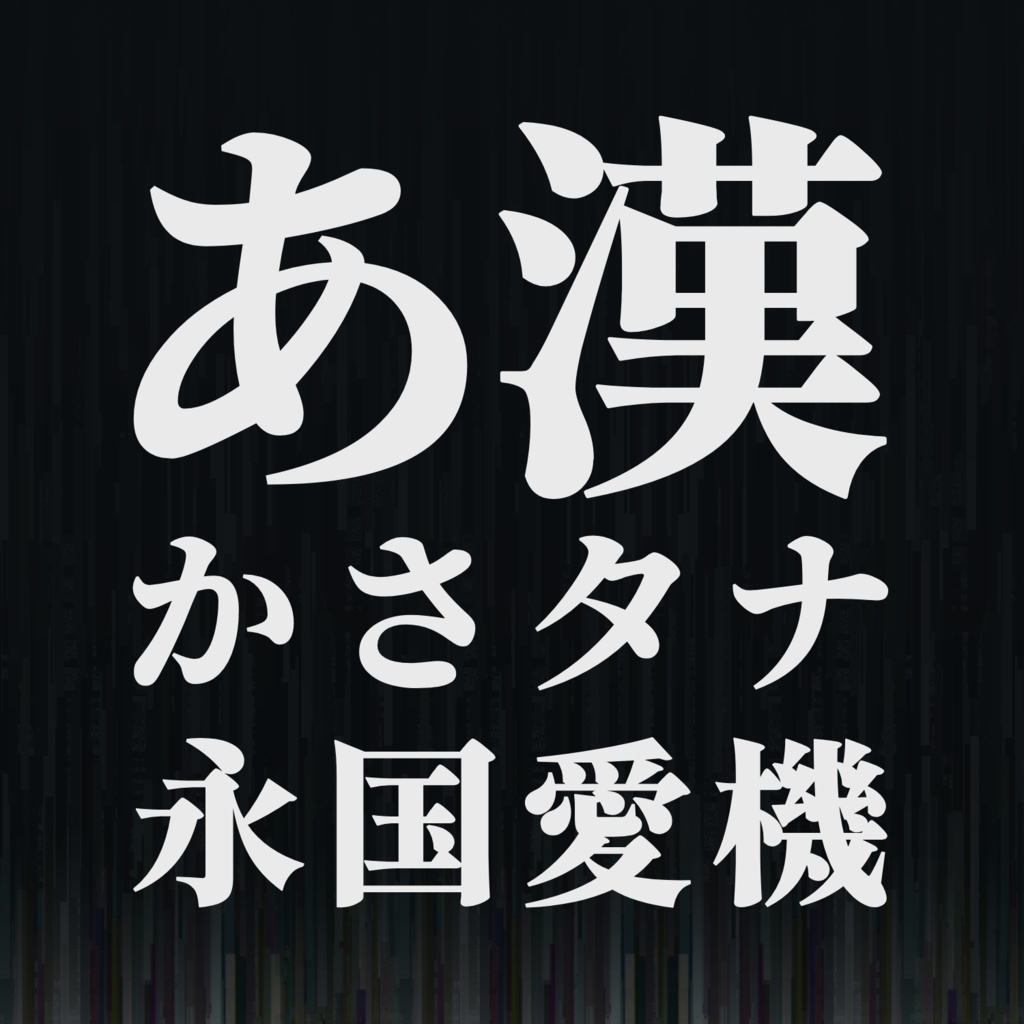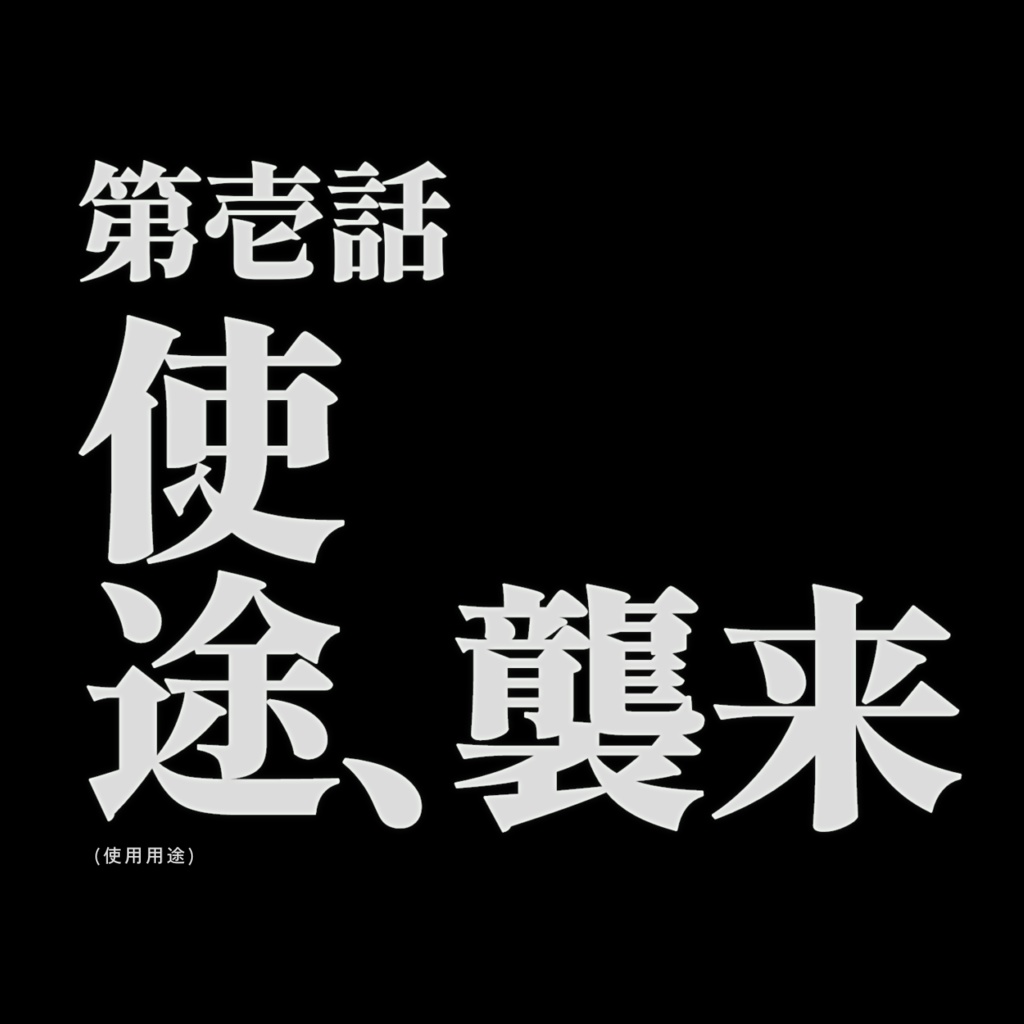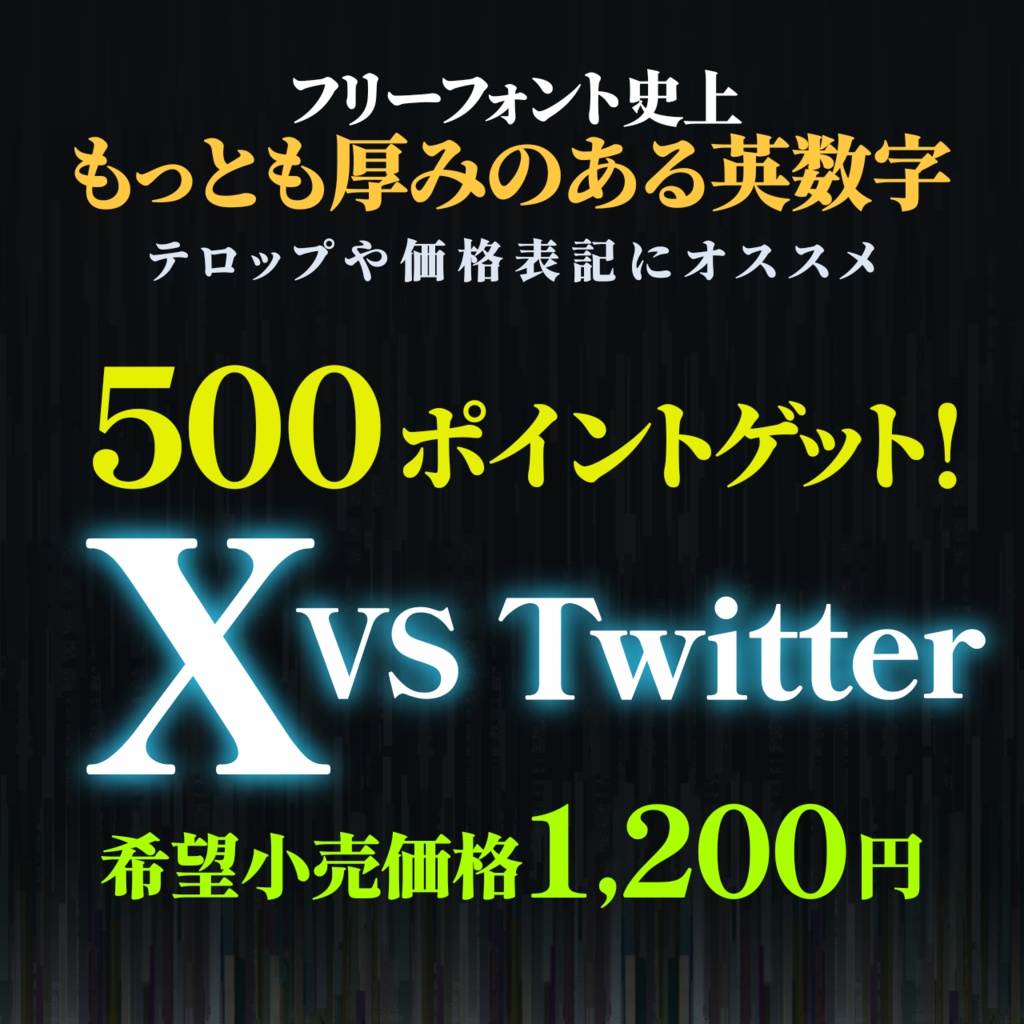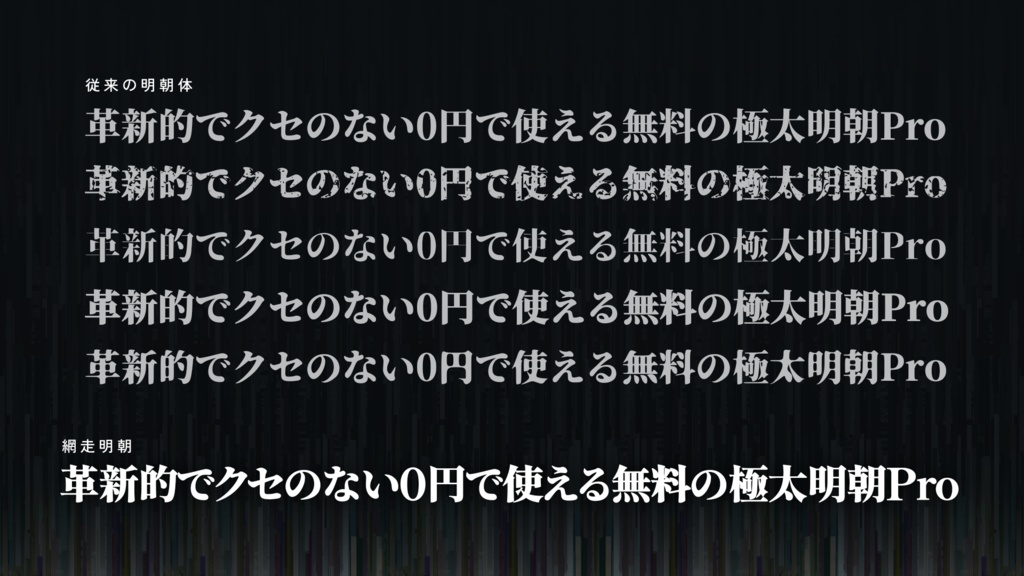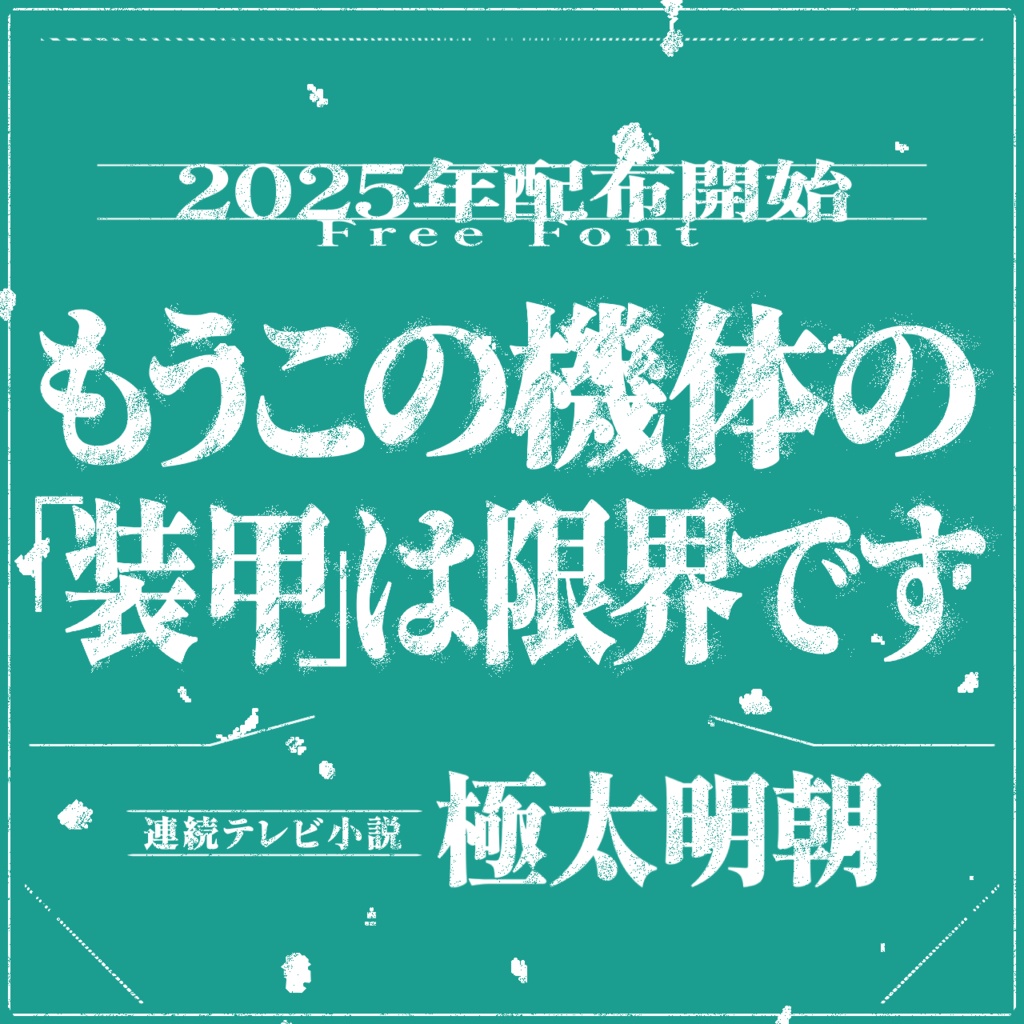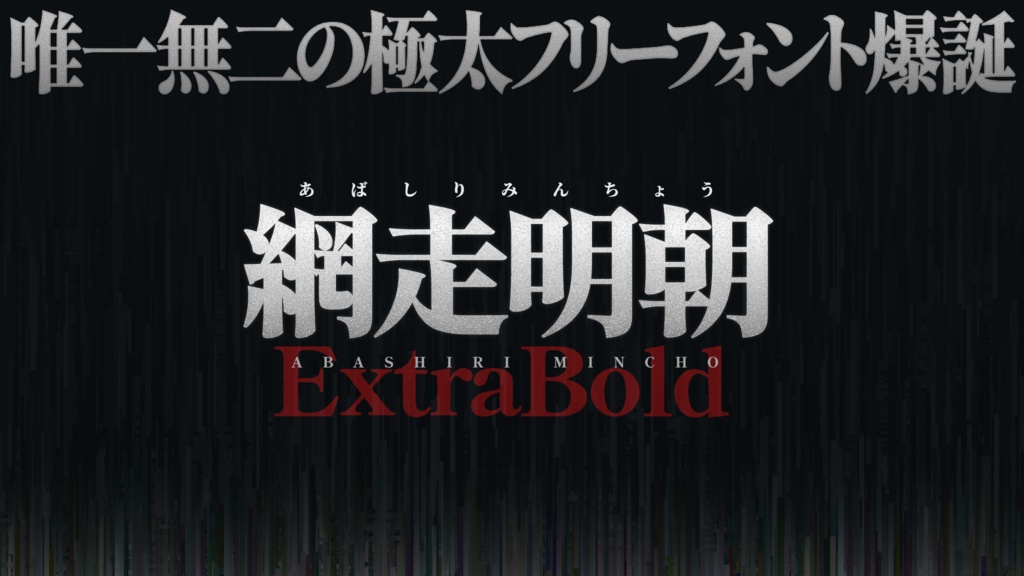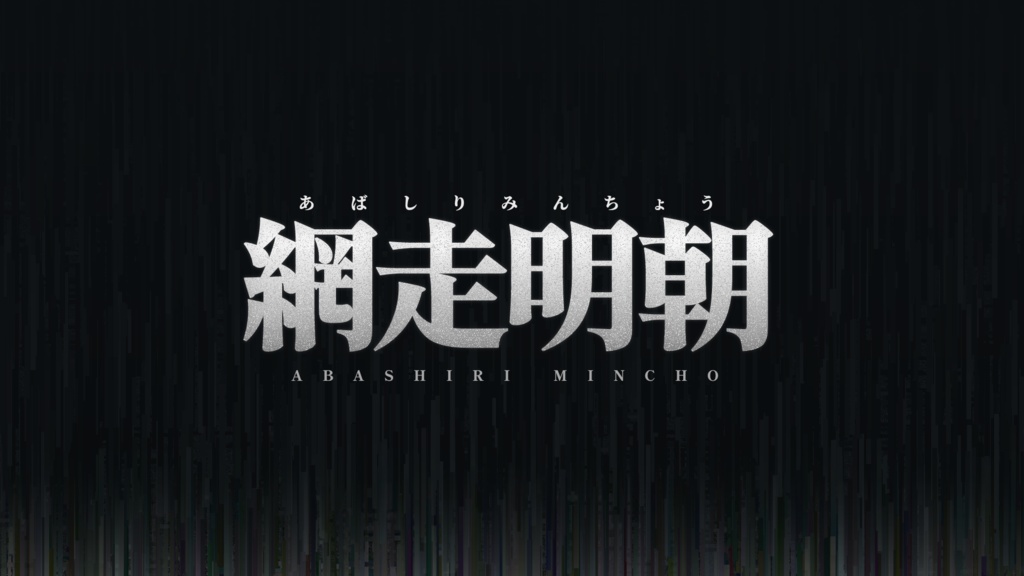
【フリーフォント】網走明朝
完全フリーの極太明朝体です。 あらゆる漢字が使えます。 商用利用もご自由に。 SIL Open Font License 1.1のもとで改変・再配布も可能です。 ■フリーの明朝体フォントで"史上最太"を実現 見出しやテロップなど、源ノ明朝 Heavyそのままでは太さが足りない場面で有効にお使いいただけます。装甲明朝や源界明朝の代替としても便利です。 ■バラエティなどでよく見るフトコロの広い英数字 フリーフォントが安っぽく見えがちな原因のひとつでもある従属欧文。網走明朝では、マティスEBを参考にした「厚み」を持たせることで、日本語の文中でも存在感を際立たせます。価格表記や点数表示にもオススメです。 ※画数の多い文字では潰れる可能性があります。重要情報の記載や本文での使用は非推奨です。 ※縦書きには非対応です。 スペシャルサンクス - 源流明朝 H - しっぽり明朝 Extra Bold - BIZ UDP明朝 Bold [2026.08.10]ver1.10 ライセンス表示および予約フォント名を整理し、OFL.txtなどの関連文書を同梱。フォント内部のライセンス情報と埋め込み設定も修正。 [2026.09.06]ver2.00 縦書きに仮対応。全角「!?」や「…」などのグリフを修正